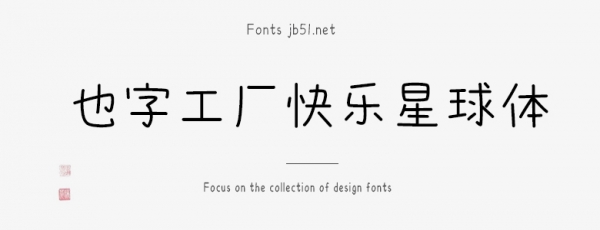
也字工廠快樂(lè)星球體是由也字工廠出品的藝術(shù)字體,字體筆觸細(xì),具有很好的視覺(jué)感,適合應(yīng)用于藝術(shù)設(shè)計(jì)、平面宣傳設(shè)計(jì)、網(wǎng)頁(yè)設(shè)計(jì),書法字帖等領(lǐng)域,需要的朋友可以前來(lái)本站下載。